31 najlepszych czcionek do plakatów (bezpłatne i premium)
Opublikowany: 2021-12-02Szukasz odważnej i interesującej wizualnie czcionki, która sprawi, że Twoje plakaty będą się wyróżniać?
Znalezienie czcionek do plakatów może być trudne, ponieważ jest ich wiele do wyboru i ważne jest, aby znaleźć czcionkę, która jest czytelna i stylowa.
Na szczęście wykonaliśmy dla Ciebie ciężką pracę i przeszukaliśmy sieć w poszukiwaniu naprawdę wyjątkowych i stylowych czcionek plakatowych.
Czytaj dalej, aby sprawdzić naszą listę 31 najlepszych czcionek do plakatów. Dołączyliśmy zarówno czcionki bezpłatne, jak i premium, więc każdy znajdzie coś dla siebie.
Czego szukać w czcionce plakatowej
Jeśli chodzi o projektowanie plakatów, ważne jest, aby projekty były atrakcyjne, przyciągające wzrok i łatwe do odczytania. Dlatego warto wybrać odważną i wyraźną czcionkę, która będzie czytelna z daleka.
Nie tylko to, ale wybrana czcionka powinna być zgodna z ogólną estetyką plakatu.
Oprócz tego powinieneś spróbować wybrać czcionkę, która będzie czytelna zarówno w małych, jak i dużych rozmiarach. W ten sposób możesz użyć go do nagłówka i mniejszych fragmentów tekstu na swoim plakacie.
31 najlepszych czcionek do plakatów
Teraz, gdy wiesz trochę więcej na temat wyboru idealnej czcionki do plakatów, przejdźmy do listy, zaczynając od naszego najlepszego wyboru…
1. Cheddar Gothic – nasz najlepszy wybór
Cheddar Gothic to rodzina prostych i odważnych czcionek, które doskonale nadają się do wykorzystania na plakatach. Rodzina czcionek obejmuje wersje czcionki Sans, Serif, Slab i Stencil, a także dodatki.
Dlaczego to nasz najlepszy wybór
Cheddar Gothic to świetna czcionka do plakatów, ponieważ jest prosta, łatwa do odczytania i wywiera wpływ. Dzięki rodzinie czcionek Cheddar możesz tworzyć różnorodne projekty do różnych celów, dlatego jest naszym ulubionym.
2. Czarno-biały krój pisma
Czarno-biały krój pisma to elegancka czcionka pędzelkowa, która świetnie wyglądałaby na stylowym plakacie. Czasami czcionki pędzla mogą być trudne do odczytania, ale czarno-biały krój pisma jest odważny i łatwy do odczytania, a jednocześnie sprawia wrażenie kobiecego rysowania odręcznego.
3. Miejsce
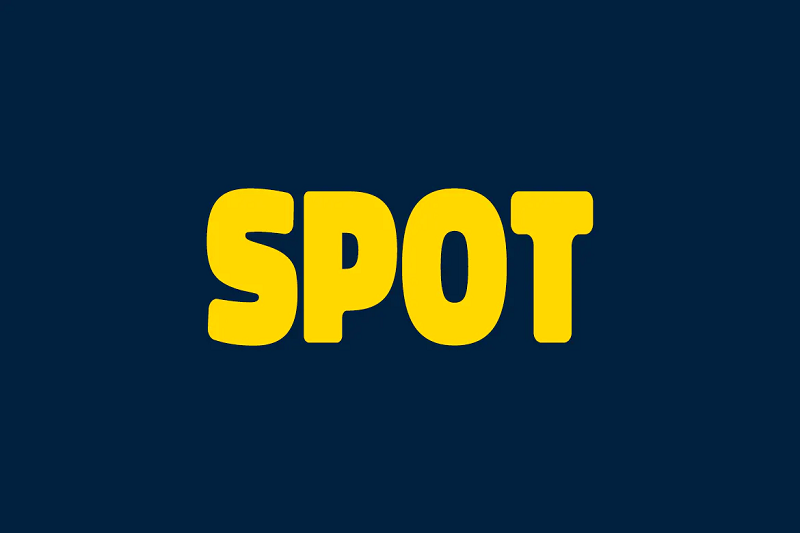
Jeśli szukasz odważnej i grubej czcionki do plakatów, Spot to świetna opcja. Ta wyjątkowa i nowoczesna czcionka z wielkimi literami naprawdę wyskakuje ze strony, dzięki czemu idealnie nadaje się do nagłówków plakatów. Pobieranie czcionki zawiera 4 wersje czcionki; Kursywa regularna, kursywa, konturowa i konturowa kursywa.
4. Skrypt Paladise Bold
Paladise to ręcznie robiony, odważny skrypt, który świetnie wygląda na plakatach i promocjach. Czcionka jest dostarczana w komplecie ze stylowymi alternatywnymi znakami, ligaturami i nie tylko, dzięki czemu można je mieszać i dopasowywać, aby tworzyć ciekawe i niepowtarzalne projekty.
5. Czcionka wypalenia
Burnout to wyjątkowa czcionka graficzna w stylu vintage. Niezależnie od tego, czy tworzysz plakaty na przyjęcie urodzinowe, czy na imprezę rodzinną, ta czcionka z pewnością wyróżni Twoje projekty. Pobieranie zawiera wszystkie znaki kapitalików, a także cyfry i znaki interpunkcyjne.
6. Kochany typ
Lovile to rodzina trzech czcionek, która doskonale nadaje się do tworzenia różnorodnych i niepowtarzalnych projektów plakatów. Rodzina obejmuje czcionki skondensowane, pogrubione i w stylu skryptu, których można używać w nagłówkach i mniejszych fragmentach tekstu plakatu. Ta zabawna i kobieca rodzina czcionek będzie świetnie wyglądać na plakatach promocyjnych lub jako element świątecznych projektów.
7. Krój Boulden
Boulden to inspirowana stylem vintage czcionka z dużymi literami, która z pewnością przyciągnie uwagę czytelnika. Czcionka przypomina stare plakaty propagandowe i byłaby idealna jako czcionka nagłówka plakatów. Pobieranie czcionek zawierało trzy style; Regularne czyszczenie, brud i cień.
8. Czcionka pędzla Rhinos Rocks
Rhinos Rocks to zabawna czcionka w stylu pędzla o męskim charakterze. Pomimo tego, że jest pochyloną czcionką pędzla, Rhinos Rocks jest nadal łatwy do odczytania i stylowy. Ta czcionka byłaby świetna do plakatów, ponieważ pobrana zawiera również stylistyczne znaki, które mogą dodać dodatkowe wizualne zainteresowanie Twoim projektom.
31. Senlita Retro czcionka wyświetlacza
Senilita to blokowa, pogrubiona czcionka, która jest idealna do nagłówków plakatów. Czcionka retro inspirowana jest włoskimi filmami z połowy wieku i wzorami art-deco. Czcionka jest dostarczana wraz z szeregiem niestandardowych ligatur.